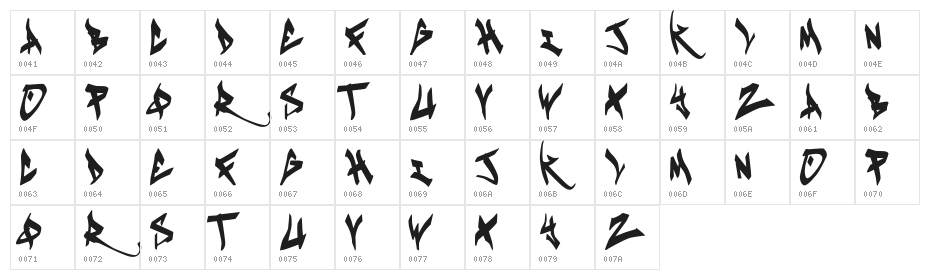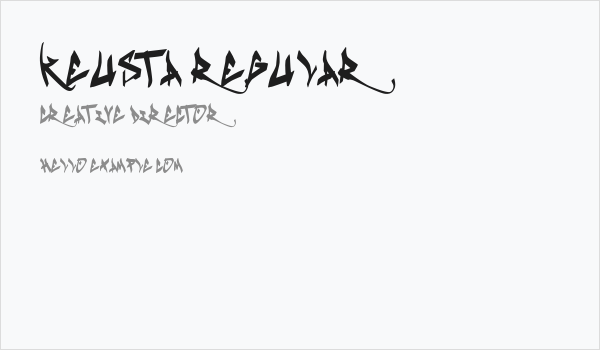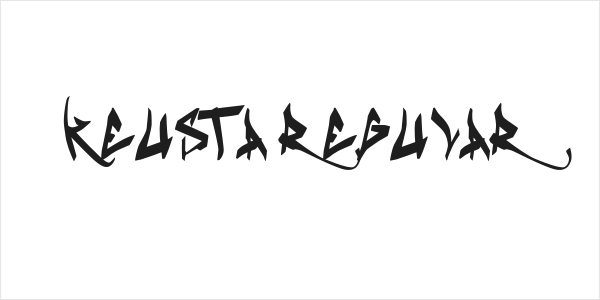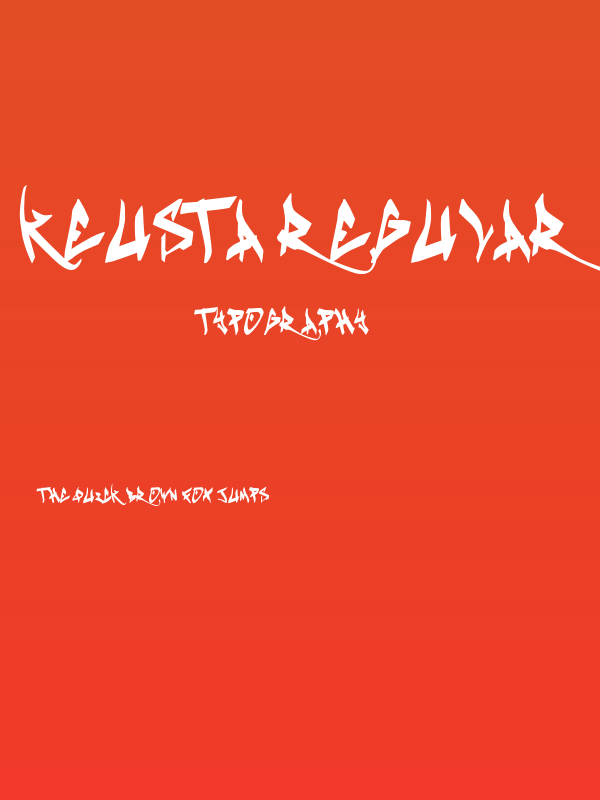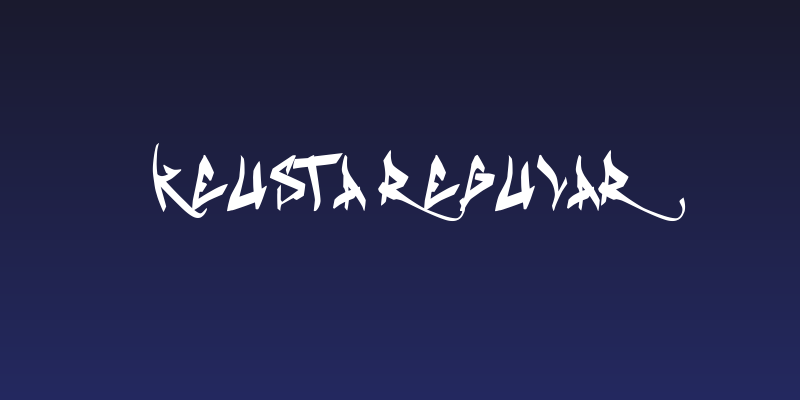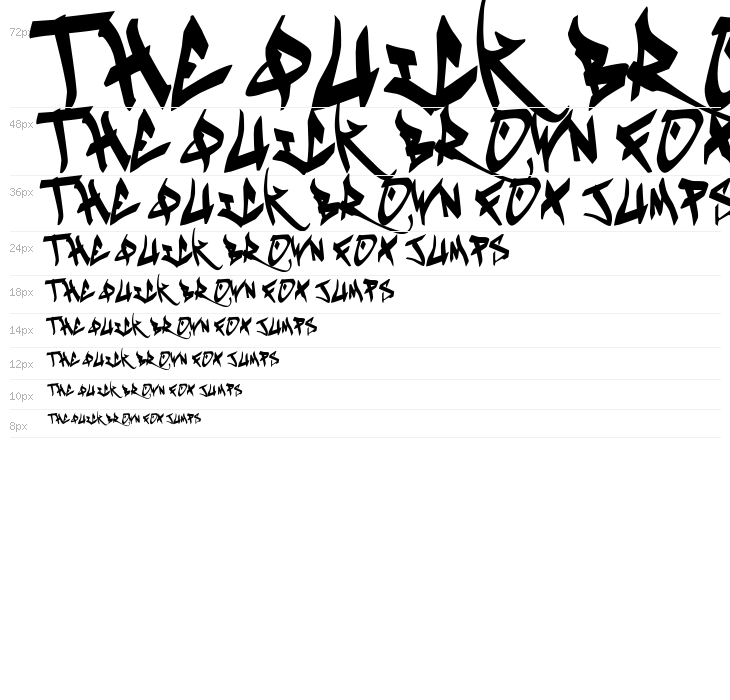
Keusta Regular Font
✎ Graffiti
| Stile generale | Modern, Urban |
| Progetti proposti | Ideal for street art designs, music album covers, urban-themed posters, and edgy branding projects. |